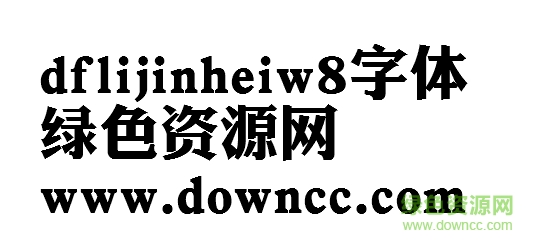
dflijinheiw8字體就是華康儷金黑W8字體的英文名稱,支持簡體中文輸入,是一個視覺體驗和表現(xiàn)力極佳的黑體字體,喜歡的朋友就請來綠色資源網(wǎng)下載吧!
dflijinheiw8 regular是華康儷金黑W8的早期版本,當時字體庫還不夠全面,部分繁體體無法正常顯示,綠色資源網(wǎng)小編推薦大家使用華康儷金黑W8字體,更好的運用于藝術設計、海報設計、排版印刷等諸多領域!
dflijinheiw8是一款線條粗黑、字體方正的華康字體,該字體適用于圖片logo、廣告設計、印刷包裝等應用!